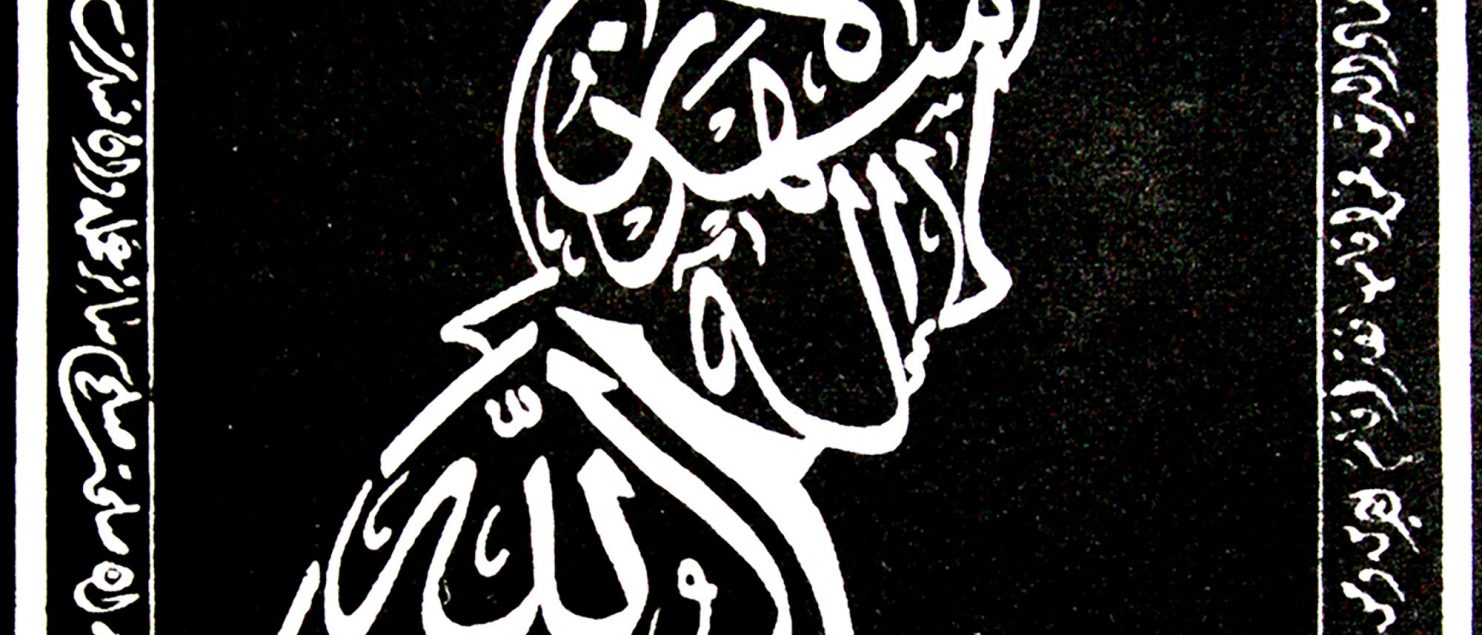
معرفی خطوط اسلامی- خطوط تفننی یا خط نقاشی
عوامل و محرکات بسیاری در شکلگیری خطوط مختلف اسلامی تاثیرگذار است، سرعت در نوشتن، زیبانویسی، تزیین و تفنن در خوشنویسی و کتابت از جمله این عوامل است که هر یک متناسب با کاربرد و حاصل ذوق و سلیقه خوشنویسان بودهاست. هنگامی که خطوط مختلف شکل میگرفت، برخی از خوشنویسان در تزیینی کردن و ایجاد تفنن در خط تلاش میکردند. تزیین در خط سابقهای طولانی دارد و انواع خطوط برای تزیین بناها، ظروف، سفالینهها و… به کار رفته که معروفترین آن خط کوفی تزیینی و بنایی است.
پس از خطوط تزیینی میتوان از خطوط تفننی نیز سخن گفت. در طول تمدن اسلامی، کاتبان و خوشنویسان در تلاش برای به تصویرکشیدن خلاقیت و نوآوری به قابلیتهای تازهای دست یافتند که یکی از نتایج آن، استفاده از تفنن در خوشنویسی است. شاید بتوان عنوان «خط نقاشی» را برای خطوط تفننی به کار برد. بدین معنا که گاه با حروف، تصویر مشخصی خلق میگشت و گاه عنصری تصویری با خط تلفیق میشد. خطوط تفننی انواع متنوعی دارد که مهمترین آن، خطوط مُشکّل، طغرا، معما، مثنی، گلزار، ناخنی و… است.
خطوط مُشکّل
تمایل به تصویری کردن خط و شکل بخشیدن به حروف، از تفننهایی است که خوشنویسان به کار میبردند و یکی از نمونههای آن، خطوط مُشکّل است. در خطوط تفننی و از جمله خطوط مُشکّل گاه از ریتم حرکات و کشیدهها برای ترسیم شکلی خاص بهره برده شده و گاه حروف به صورت قرینه و متقارن به کار رفته است. در برخی از چرخاندن حروف برای ترسیم شکلی خاص استفاده شده است. در خطوط مُشکّل، بر جنبه بصری خط تأکید شده و تصویر همراه با خط دیده میشود و حتی گاه بر خط اولویت یافته به شکلی که در نگاه اول تصویر دیده میشود و از این لحاظ، عنوان خطوط مُشکّل برای این گروه از خطوط تفننی به کار رفتهاست. بدینگونه که تصویری از یک شیر یا پرنده با حروف خلق شدهاست. یکی از معروفترین نمونههای خطوط مُشکّل، مرغ بسم الله است.
طغرا
شیوهای است که برای اسامی پادشاهان و سلاطین در بالای نامهها و فرامین کتابت میشد. در خط طغرا، «الف»ها در کنار قوسهای بلند دوایر و کشیدهها به یکدیگر اتصال یافتهاند. استفاده از فرم منحنی و اتصالات پیچیده حروف، مهمترین ویژگی بصری خط طغرا است و حالت امضا داشته است (امضا سلاطین و پادشاهان). طغرانویسی با هر خطی امکانپذیر است اما بیشترین خطی که با آن طغرا نوشته شده، دیوانی و ثلث است.
معما
خطی است که به شکل تفننی به گونهای رمزآلود و معماگونه نوشته شدهاست، به شیوهای که خواندن آن دشوار است. شاید بتوان سابقه معمانویسی در خط را در میان کاتبان دیوانهای سلطانی و دفاتر قضاوت یافت. آنها میبایست نوشتهها را طوری مینوشتند که در دسترس دیگران قرار نگیرد. معما در خط، آن است که جمله یا عبارتی را از روی تفنن، طوری نویسند که خواندنش مشکل و محتاج دقت باشد و به طور عادی برای هر بینندهای، خوانا نیست بلکه تا حدودی به صورت پیچیده نوشته شده و خواندن آن، نیازمند تأمل بیشتری است.
مثنی
مثنی به معنای دوتایی، جفت و کتابت به شکل توأمان است به گونهای که حروف با یکدیگر قرینهاند. در مثنی، دقت ترسیم حروف و قرینگی بسیار حائز اهمیت است.
گلزار
یکی از انواع خطوط تفننی است و در آن فضای داخل حروف با نقوش گیاهی، تزیینی و یا حیوانی پر شدهاست.
در برخی از خطوط تفننی، بخشهایی از کلمه مانند شروع و ابتدای حروف با تقش گیاهی و تزیینی همراه شدهاست. گویی حروف، نقاشی شده و اثرات گردشهای قلمنی کمتر است. ریشه و سابقه تلفیق نقوش گیاهی با حروف را میتوان در کوفی تزیینی یافت.
خط ناخنی
شیوهای تفننی است که از ناخن برای کتابت استفاده شدهاست. در کتابت و خوشنویسی از ابزارهای متنوعی برای کتابت استفاده شده و یکی از این ابزارها که برای تفنن به کار رفته ناخن ( انگشت سبابه یا میانه به همراه انگشت شست) است که سبب ایجاد فرورفتگی و برجستگی روی کاغذ شدهاست.
در پایان باید خاطر نشان کرد که خطوط تفننی فقط نمونههایی که به آن اشاره شده را شامل نمیشود بلکه ممکن است نمونههای متنوع دیگری از خطوط تفننی نیز وجود داشته باشد و در این مقاله تلاش شده مهمترین این خطوط بررسی و استخراج گردد. یکی از شیوههایی که در منابع از آن به عنوان خطوط تفننی یاد شده سیاهمشق است. با این حال نگارنده معتقد است با توجه به این که سیاهمشق نخست با هدف تمرین خوشنویسان بوجود آمده و سپس به مرور بر ویژگیهای زیباییشناسانه آن به عنوان هنر اصیل و فاخر خوشنویسی تأکید شده بهشکلی که خود مجردا یک قالب هنری محسوب میشود، بهتر است از توضیح آن در مقاله حاضر پرهیز نموده تا در مقاله دیگر مفصلا درباره این شیوه فاخر خوشنویسی تحقیق شود.